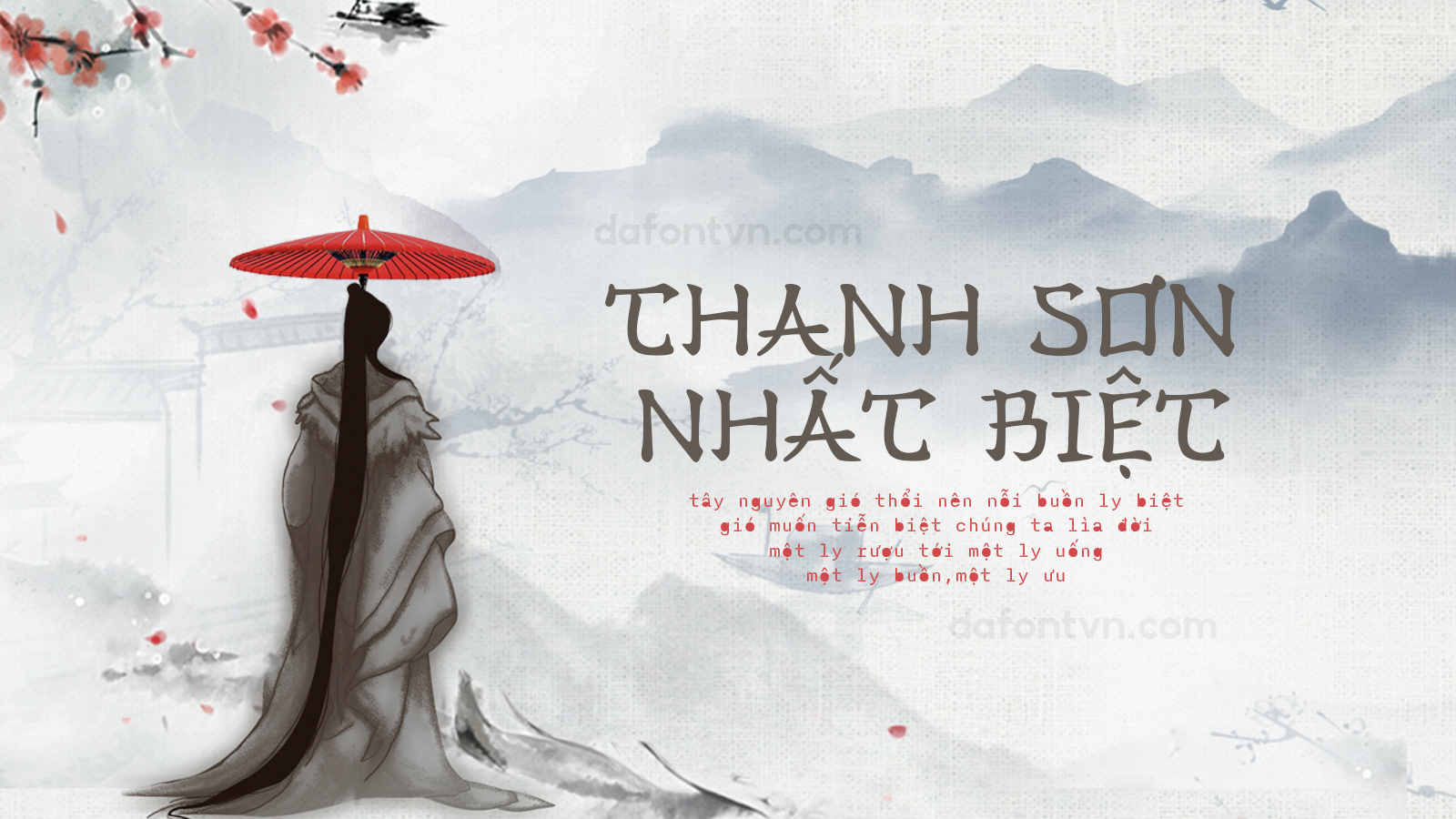
Font Han Zi Việt Hóa - Font chữ cổ trang
Font Han Zi được lấy cảm ứng từ các ký tự tượng hình truyền thống của Trung Quốc đã được tác giả tìm hiểu kỹ lưỡng bằng cách sử dụng các phím của hệ thống chữ Kaishu thông thường mang đến một kiểu chữ chân thực về mặt phong cách.
Font Han Zi Việt Hóa rất phù hợp với các thiết kế cổ trang, bạn có thể sử dụng font này để thiết kế bìa sách, typo, cover hoặc bất kỳ thiết kế nào khác.
Font Han Zi Việt Hóa
Font cổ trang Han Zi việt hóa